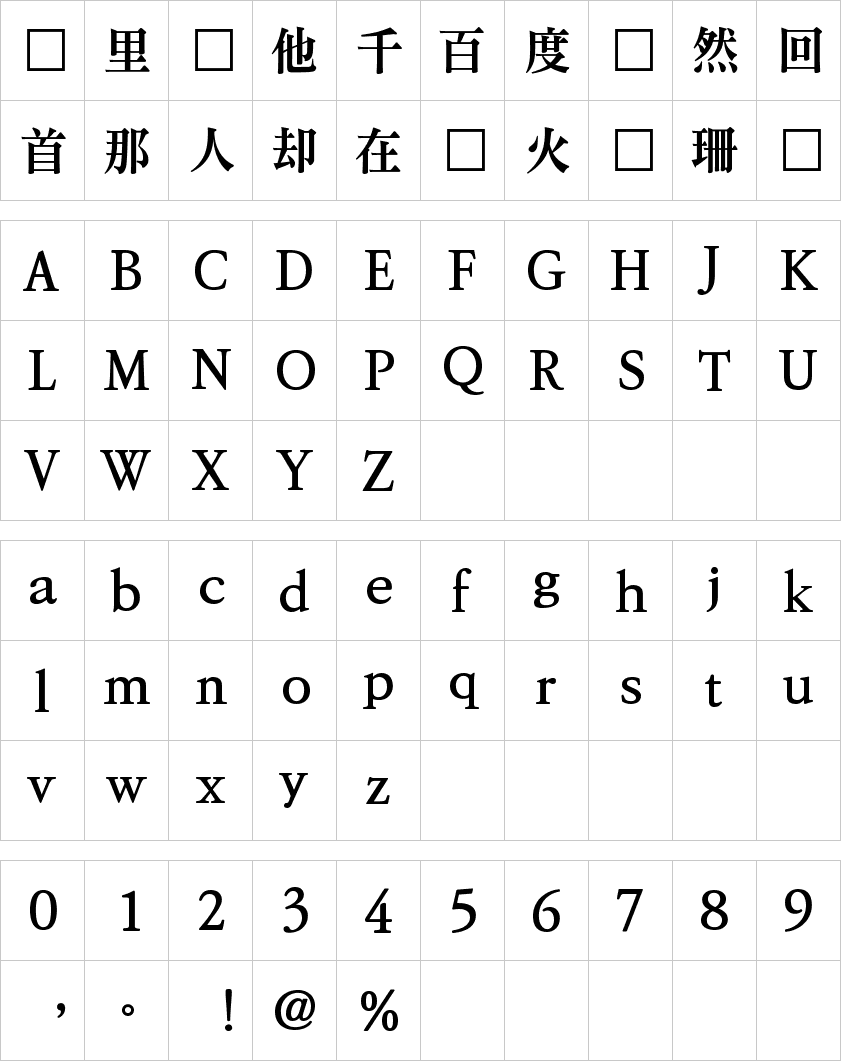
KoPubWorld바탕체
与书籍和报纸等印刷材料不同,电子书只能在数字屏幕上查看,因此需要专门的字体。因此,韩国出版商协会在 2011 年开发并免费分发了“KoPub Font”,以加强出版商的电子出版内容制作和振兴电子书市场。
“KoPub 字体”在数字屏幕上显示出与印刷材料相当的可读性,并被定位为用于 IT、电影和广告设计等各种行业以及出版界的最佳字体。
2019 年,“KoPub 字体”重制为“KoPub World 字体”。
“KoPub World 字体”包括扩展汉字、日文、拉丁文、俄文、希伯来文、阿拉伯文、梵文等多种语言以及以前没有实施过的旧韩文,读者可以通过它享受更广泛的知识和文化生活。
我们期待通过“KoPub World字体”将优秀的国内内容引入国外,并向我们的读者传播世界各地的各种外国书籍。